Im Norden treffen sich phönizische, griechische, römische und arabische Spuren; in der Sahara leben die Tifinagh-Zeichen der Tuareg; in Äthiopien blüht das Geʿez seit über 1500 Jahren als liturgische Schrift. In Westafrika trugen Adschami und später lateinbasierte Alphabete dazu bei, Sprachen wie Hausa oder Fulfulde aufzuschreiben.
Nordafrika und Sahara, Westafrika und Sahel, Horn von Afrika und das südliche Afrika: Jede Region erzählt ihre eigene Schriftgeschichte — geformt von Klima, Karawanenwegen, Königreichen und Religionen.
Eine Karte, viele Geschichten
Schrift in den Regionen Afrikas
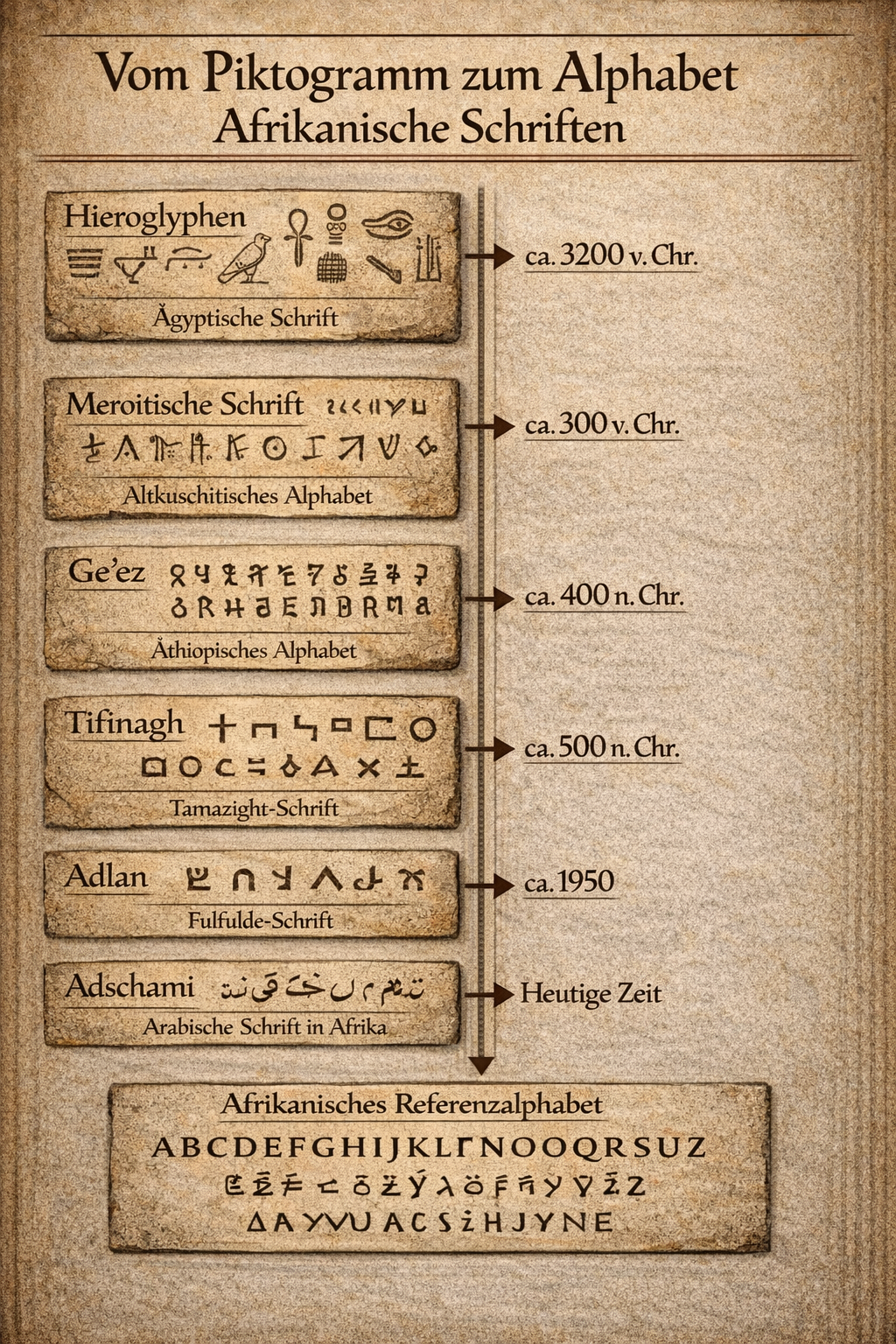
Vom Mittelmeer bis zum Kap
Die Karte zeigt die wichtigsten Schriftregionen Afrikas: arabisch geprägte Küsten, Berber-Hochländer, Sahelzone und das äthiopische Hochland. Jede dieser Zonen entwickelte eigene Antworten auf die Aufgabe, Sprache sichtbar zu machen.